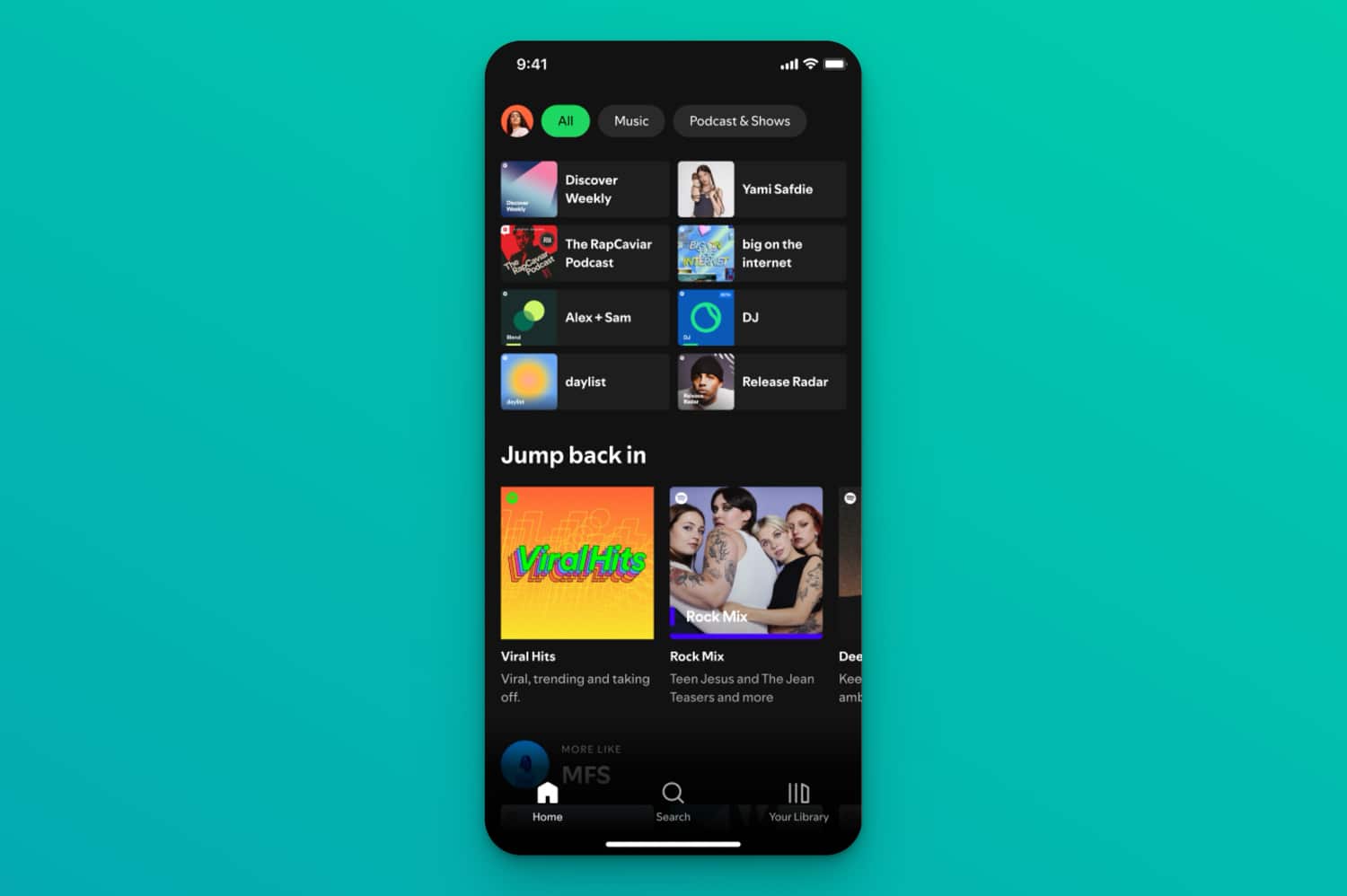
Spotify: Neue Schriftart soll in der ganzen App zur Anwendung kommen
"Spotify Mix" sorgt für visuelle Änderungen
Neue Spotify Mix-Schriftart mit verschiedenen Anwendungsbeispielen
Das neueste Update von des Musikstreaming-Dienstes Spotify (App Store-Link) verändert die App in visueller Hinsicht. Spotify Mix – die neue, maßgeschneiderte Schriftart des Unternehmens – wird seit gestern eingeführt und ersetzt die Circular-Schriftvariante, die Spotify aktuell noch in der eigenen App und auf dem Desktop verwendet.
Der leicht verwirrende Name ist eine Hommage an die „dynamische und sich entwickelnde Natur der Audiokultur im Laufe der Jahre“, so Rasmus Wängelin, Global Head of Brand Design bei Spotify, in einer Pressemitteilung. Spotify Mix hat man in Zusammenarbeit mit der Berliner Schriftgießerei Dinamo Typefaces entwickelt. Laut Wängelin ist das neue variable Schriftdesign „im wahrsten Sinne des Wortes ein Remix“, der aus der Verschmelzung von Elementen aus verschiedenen Schriftstilen entstanden ist. Wängelin berichtet weiter:
„Das Ergebnis ist eine serifenlose Schrift, die Merkmale klassischer und zeitgenössischer Stile miteinander verbindet und so ein unverwechselbares und einzigartiges Aussehen schafft. Wir haben auf subtile Weise die Formen von Schallwellen integriert, um ein rhythmisches Gefühl zu erzeugen. Die Kombination aus scharfen Winkeln und sanften Kurven verleiht der Schrift einen unverwechselbaren Charakter, der ganz im Sinne von Spotify ist.“
Neue Spotify Mix-Schriftart auf einem iPhone
Das Unternehmen beabsichtigt, Spotify Mix für alles zu verwenden, von Wiedergabelisten bis hin zu Marketingkampagnen. Da es sich um eine variable Schrift handelt – Breite, Neigung und andere Variablen können geändert werden, ohne dass separate Dateien erforderlich sind – sollte es für Spotify sehr einfach sein, sie anzupassen. Damit ist auch eine gewisse kreative Flexibilität gegeben, so dass Elemente wie Playlist-Cover, Promos und andere Inhalte abwechslungsreicher erscheinen, aber dennoch ein einheitliches Design aufweisen.
Auch die Wortmarke im Spotify-Logo wird auf die neue Schriftart aktualisiert: Sie ist bereits auf dem Nachrichtenportal des Unternehmens zu sehen. Sprachen mit lateinischen Schriften und schriftliche Inhalte in Vietnamesisch werden die ersten sein, die Spotify Mix verwenden. Laut Spotify soll die neue Schriftart „in den kommenden Wochen“ schrittweise eingeführt werden.